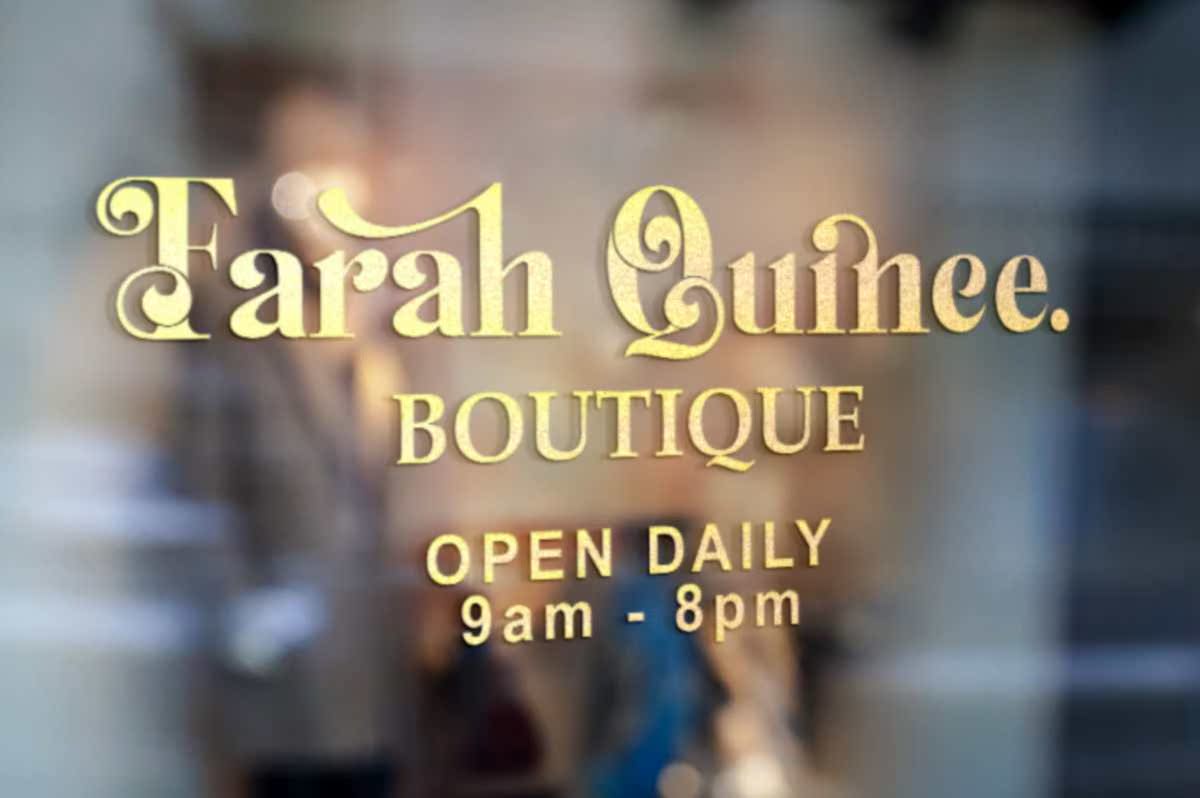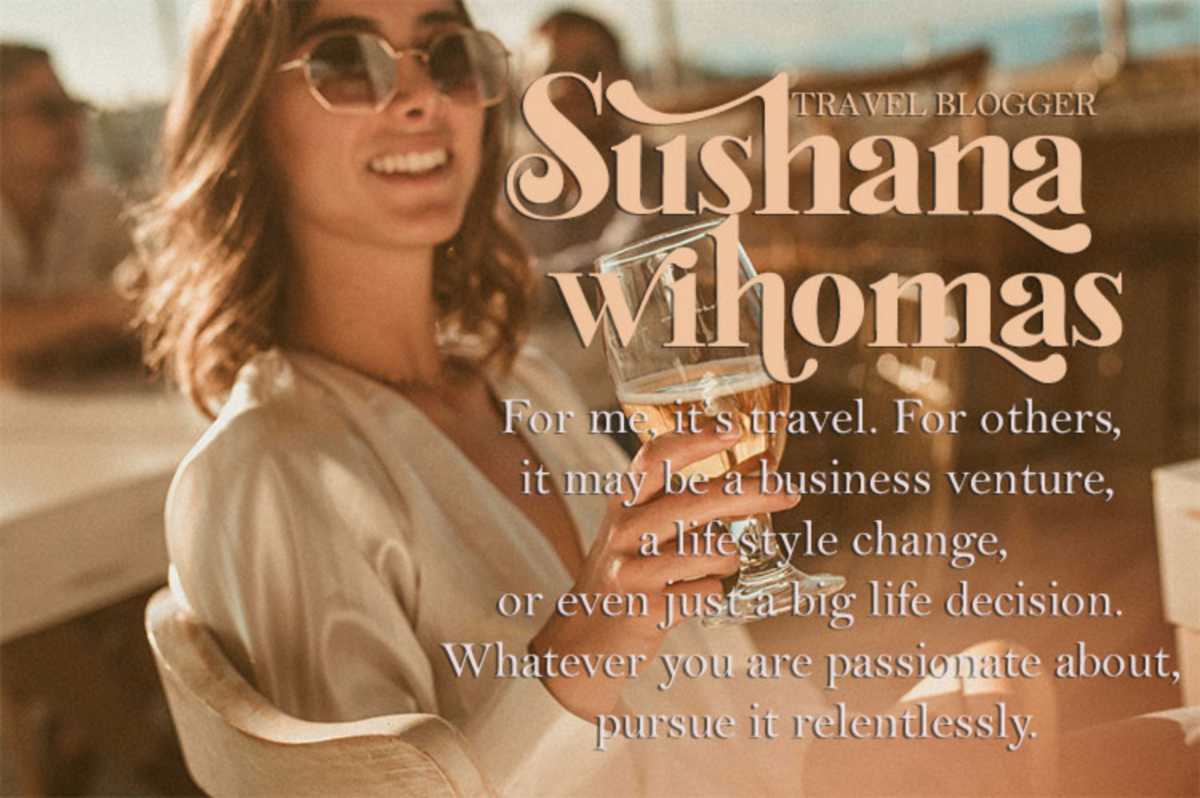
Bughia Serifont是一款大写和小写的字体,带有平衡的曲线。这种字体是由古时的文字创作而来的,但现在仍然有着惊人的现代感。各种款式可选,可用于多种设计,适用于标题、徽标、海报、包装、T恤、明信片、,还有更多。Bughia Serifont是一款大写和小写的字体,带有平衡的曲线。这种字体是从古时开始创作的,但现在仍然有着惊人的现代感。各种风格的替代品都允许多种多样的设计选项,并完美地适用于标题、徽标、海报、包装、T恤、明信片等。